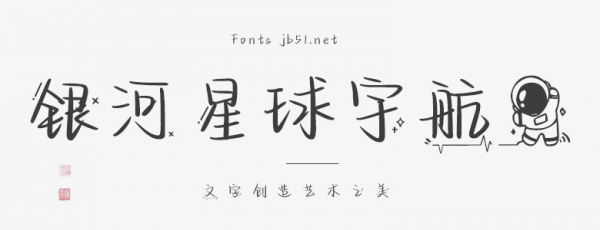
銀河星球宇航員字體是一款極具創(chuàng)意和想象力的字體。設計靈感來源于宇宙的神秘和浩瀚,以及人類對太空探索的渴望。字體的每個字母都像是一個宇航員,帶領著我們穿越星際,探索未知的宇宙。 字體的線條流暢、簡潔,給人一種科技感和未來感。每個字母的形狀和比例都經過精心的設計,以確保在保持字體的辨識度的同時,也能展現出宇航員在太空中的自由與靈動。 銀河星球宇航員字體的實用性也非常高。適合用于各種文本大小的排版,無論是用作標題還是正文,都能夠展現出其獨特的風格和個性。尤其在科技、航空、宇宙探索等主題的場合中使用,更能激發(fā)人們的想象力和探索精神。 總的來說,銀河星球宇航員字體是一款充滿創(chuàng)意和未來感的字體,它將帶領我們進入一個全新的、未知的宇宙世界。希望這款字體能夠在你需要的時候,為你的設計增添一份獨特的魅力和個性。